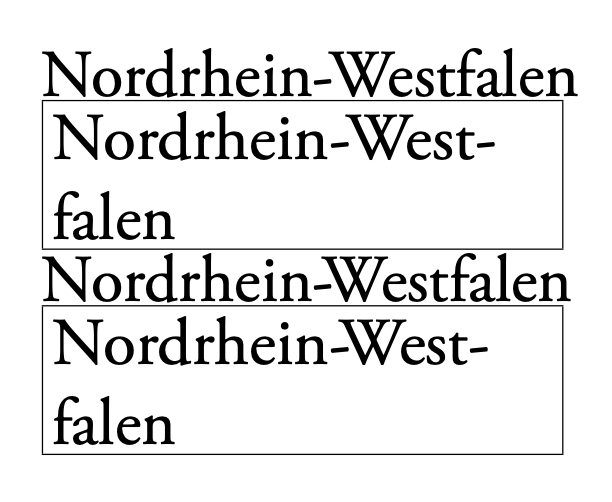
Kerning, Bindestriche, Silbentrennung und LuaLaTeX
Ich bin gerade mit meinem Latein am Ende. Ich habe zwei Tage rumgefrickelt, weil mir im Wort "Nordrhein-Westfalen" die große Lücke zwischen dem Bindestrich und dem großen W nicht gefiel. Also habe ich mir ein Minimalbeispiel gebastelt und ein bisschen am Kerning 'rumgefummelt bis mir der Abstand gefiel. Das war etwas frickelig, weil meine Schrift (EB Garamond) mehrere Zeichen für den Bindestrich benutzt, je nachdem, ob Versalien oder Gemeine im spiel sind. Aber wie immer habe ich etwas gelernt dabei. Jetzt wollte ich meine Errungenschaft (ein selbst definiertes Lua-Feature) mal auf den eigentlichen Text loslassen und es funktionierte nicht. Also wieder etwas rumgefrickelt und dann fiel es mir wie Schuppen von den Augen: Im eigentlichen Text wird kein normale Bindestrich gesetzt. Hintergrund ist, dass LaTeX Wörter mit Bindestrich in der Regel nur am Bindestrich trennen kann. Deswegen setzt man dann einen "Bindestrich mit Trennungserlaubnis". Im Code steht dann "Nordrhein"=Westfalen". Und auch wenn das im Endergebnis den gleichen Bindestrich ergibt wie "Nordrhein-Westfalen" funktioniert mein Lua-Feature dann nicht - ganz offenbar weil der Bindestrich dann noch nicht existiert, wenn das Kerning-Feature angewandt wird. Mein Lua-Feature sieht wie folgt aus:
Und jetzt die Frage aller Fragen: Wie lösen wir das Problem? Kann ich LuaLaTeX irgendwie beibiegen, das Feature zu einem späteren Zeitpunkt anzuwenden - sprich: Wenn "= bereits gegen den Bindestrich ausgetauscht ist?
Irgendwie erinnert mich das Basteln von Lua-Features immer so ein bisschen an das Sprachenlernen mit Duolingo. Man macht das nach, was man irgendwo findet (bzw. vorgeplappert kriegt), aber irgendwie findet sich kaum eine systematische Übersicht.
Wie lösen wir das Problem?
Kurzfassung vorweg: Ein OpenType-/Lua-Fontfeature ist dafür der falsche Ort. Fontfeatures werden angewandt, bevor aus dem Eingabestrom Diskretionsknoten (disc) mit einem realen Bindestrich entstehen. Du kannst das Feature nicht „nach hinten verschieben“. Die saubere Lösung ist, den Diskretionsknoten selbst zu behandeln, also auf LuaTeX-Node-Ebene nach der Umsetzung von = zu einem Trennstrich einzugreifen.
Jetzt etwas ausführlicher und systematisch.
1. Was genau passiert technisch
– In der Eingabe erzeugt = keinen Glyphenknoten.
– LuaTeX erzeugt stattdessen einen disc-Knoten (discretionary).
– Erst bei der Zeilenumbruchphase wird daraus im „no-break“-Fall ein Glyphenknoten mit dem Hyphen-Zeichen der aktuellen Schrift.
– OpenType-Features (auch Lua-Features vom Typ kern) laufen deutlich früher, nämlich beim Aufbau der Glyphenliste aus Zeichen.
– Dein Feature sieht deshalb den Hyphen nie, weil es zu diesem Zeitpunkt schlicht keinen gibt.
Das ist kein Bug, sondern Teil der Pipeline. Ein Fontfeature kann prinzipiell nicht auf etwas reagieren, das erst später materialisiert wird.
1. Warum „Feature später anwenden“ nicht geht
LuaLaTeX kennt keine Möglichkeit, ein Fontfeature nach der Diskretionsauflösung erneut auszuführen. Features sind an die Fontverarbeitung gekoppelt, nicht an den Zeilenumbruch. Es gibt also keinen Schalter wie „apply_feature_after_disc“.
1. Der richtige Ansatz: disc-Knoten behandeln
Wenn du das Kerning zwischen Hyphen und folgendem W beeinflussen willst, musst du:
– auf Node-Ebene arbeiten
– einen Callback verwenden, der nach der Erzeugung der disc-Knoten läuft, aber bevor die finale Ausgabe erfolgt
Die üblichen Kandidaten sind:
– pre_linebreak_filter
– hpack_filter
In diesen Callbacks kannst du:
– disc-Knoten erkennen
– den „no_break“-Teil des disc untersuchen
– dort gezielt ein Kern-Node nach dem Hyphen-Glyph einfügen oder dessen Breite verändern
Konkret: Du prüfst, ob der disc im no_break-Fall einen Hyphen-Glyph erzeugt und ob direkt danach ein Glyph mit Unicode W (oder Glyph-ID von W) folgt. Dann fügst du einen Kern-Node mit negativer Breite ein.
1. Skizze der Logik (konzeptionell, nicht als Drop-in-Code)
– Iteriere über die Node-Liste im pre_linebreak_filter.
– Wenn
node.id == disc:
– hole disc.nobrk
– prüfe, ob disc.nobrk mit einem Hyphen-Glyph beginnt
– prüfe den folgenden Node im Hauptstrom auf Glyph W
– füge zwischen Hyphen und W einen kern-Node ein
Damit arbeitest du exakt zu dem Zeitpunkt, an dem dein Problem real existiert.
1. Alternative, wenn es nur um diesen einen Fall geht
Falls du wirklich nur „-W“ in genau diesem Kontext brauchst, gäbe es auch typografische Workarounds:
– explizites \kern nach dem = (unschön, aber robust)
– eigenes Makro für solche Zusammensetzungen
– oder ein fontinternes Paar für Hyphen+W und dann bewusst auf = verzichten
Aber technisch sauber und generalisierbar ist eindeutig der disc-Ansatz.
1. Fazit
– Nein, ein Lua-Fontfeature kann nicht auf = reagieren und auch nicht „später“ ausgeführt werden.
– Dein Verständnis ist korrekt: Der Bindestrich existiert beim Feature-Lauf noch nicht.
– Die Lösung liegt nicht im Font, sondern im Node-Callback.
– pre_linebreak_filter oder hpack_filter sind der richtige Ort.
– Dort behandelst du disc-Knoten gezielt und fügst das gewünschte Kerning manuell ein.
Wenn du willst, kann ich dir im nächsten Schritt einen minimalen, funktionierenden Lua-Code für genau diesen disc-Fall formulieren, sagt ChatGPT …
Die Abbildung zeigt oben die Ausgabe ohne und unten mit neuem Kerning, jeweils ohne und mit Trennung.